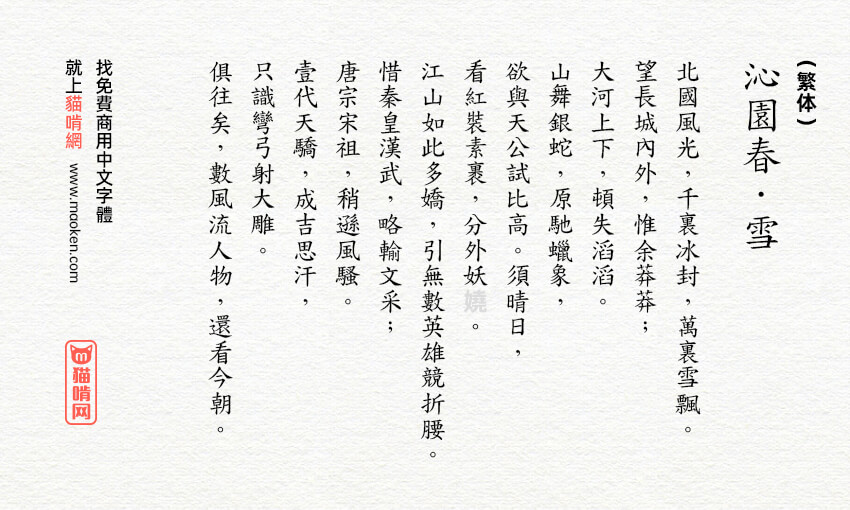
免费香港楷书:中国香港人造香港字 香港本土字形
字体作者:香港开源项目 (中国香港) 字体字重:1个
免费香港楷书是由“香港圣公会麦理浩夫人中心-林植宣博士老人综合服务中心”及“香港创意开放科技协会所”合办的一项大型开源合作项目。透过项目,组织了一群对资讯科技有兴趣的退休长者,透过共同的合作、讨论、实践、参与,制作出符合现今香港教育需要的中文电脑楷书——《免费香港楷书》,以克服香港教育界中正面对著中文电脑字体与香港中文书写差异的障碍。
免费香港楷书(Free HK Kai)是根据香港特别行区教育局课程发展处中国语文教育组于2012年所编制出版的《常用字字形表(2007年重排本)》为楷书字型基础作出修改。
本字型为免费香港楷书4700字版,根据《常用字字形表(2007年重排本)》共有4,762个小学生常用字。
本字型修改来源于台湾全字库正楷体。
好可惜,这款字体很多字不能识别。没办法用在大量文字内容产出的地方
然而香港又有新標準了 港版思源黑99%按照的是新標準 餘下的1%(如 聽 瓊)是思源自身映射錯誤 這個楷書延續舊標準 估計不會更新了
我們日常使用的字型寫法為台灣標準,但香港政府早於八十年代時藉著「中文字」的學習需要與不同大學院校的學者共同研究,並頒布了香港中文字的寫法,以方便老師教授學童學習中文字。但時至今日,香港並未有一套開源、且跟從香港教育局指引的中文電腦字型可供大眾使用。經過我們這一年的努力,已於2016年冬至公佈了「自由香港楷書4700字版」的下載,而最終目標是能完成二萬多字的完整中文開源楷書字型。
「自由香港字型」獲得ICT AWARDS 2017「最佳生活時尚(學習、生活)銅獎」及「特別嘉許(樂活銀髮)」兩項獎項。
• 我查阅他们发起这个字体的初衷,是香港一班退了休的长者一起做的字。中国香港现在很多字体都是使用中国台湾的字库,文字的写法上有很多不同。所以他们拿全字库改进行修改,就是现在的这款自由香港楷书。到2017年之后都不见他这套字体有继续更新了。